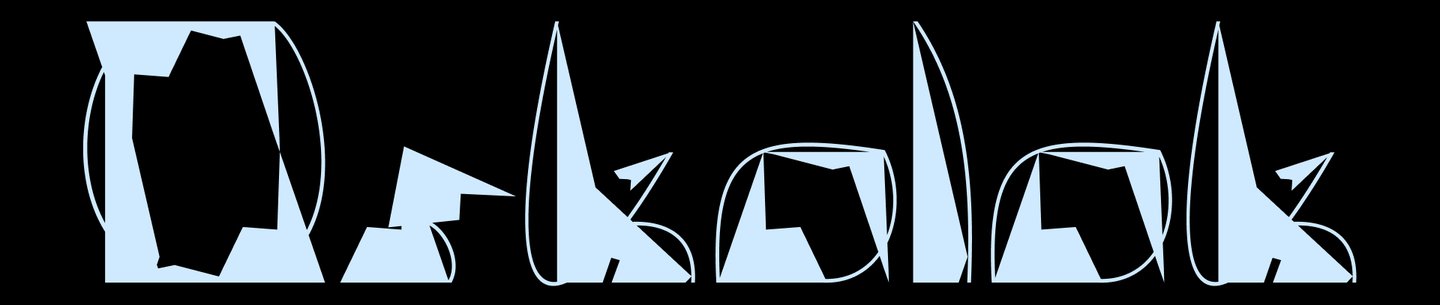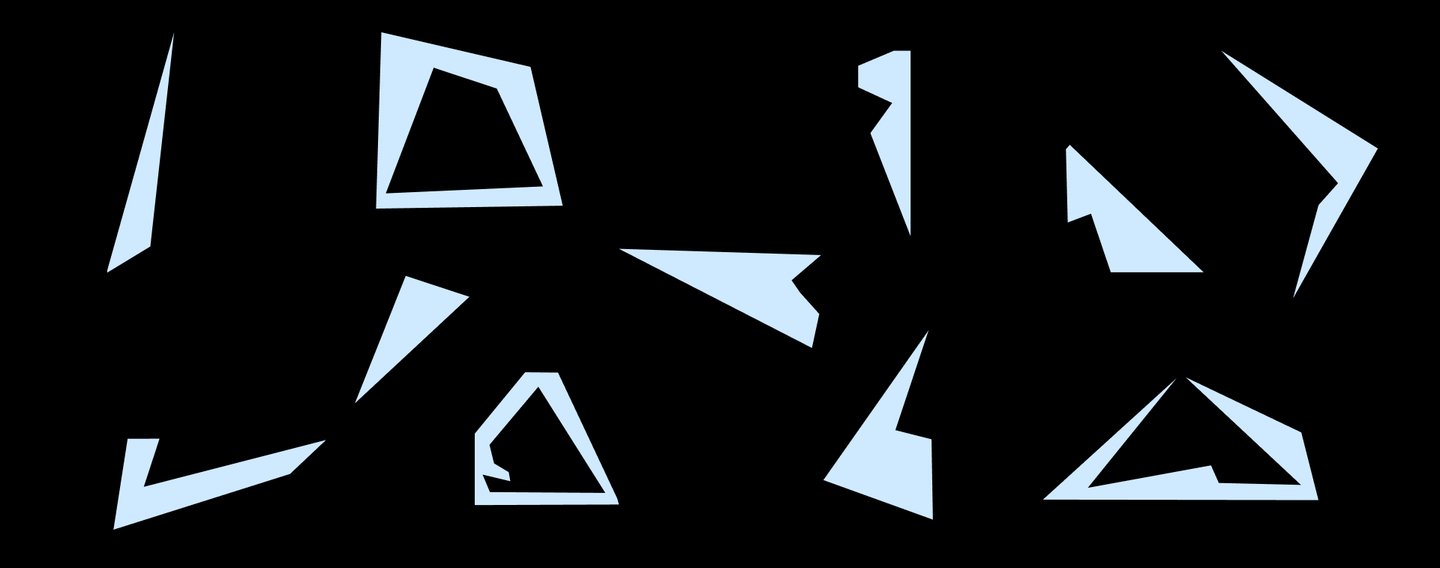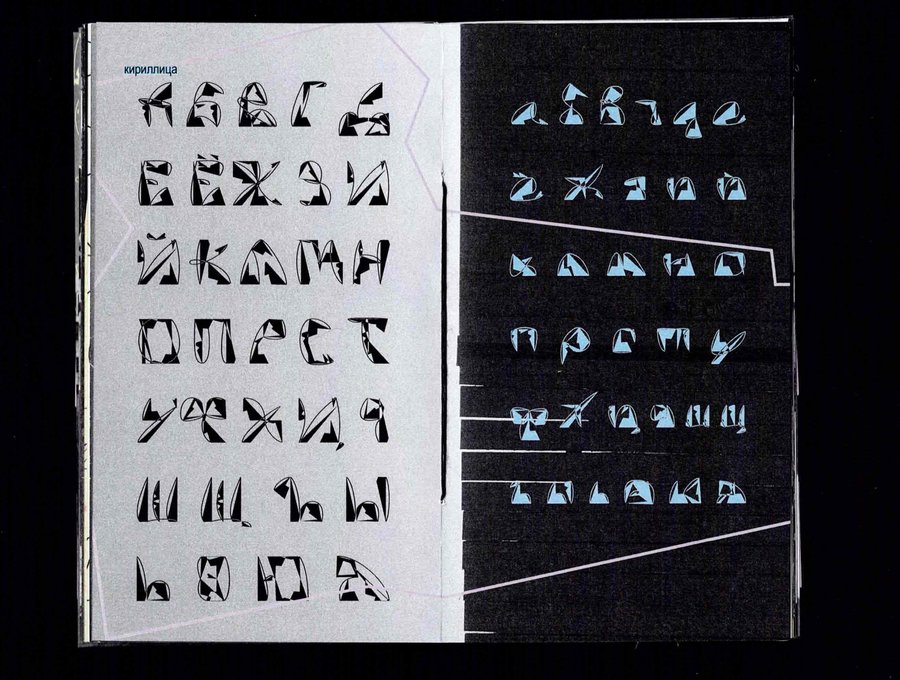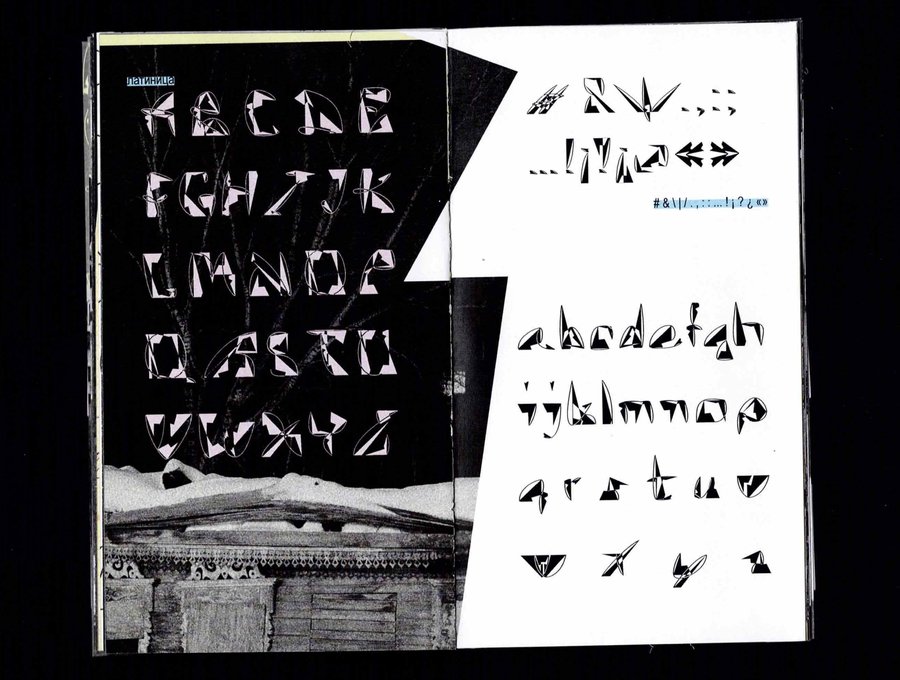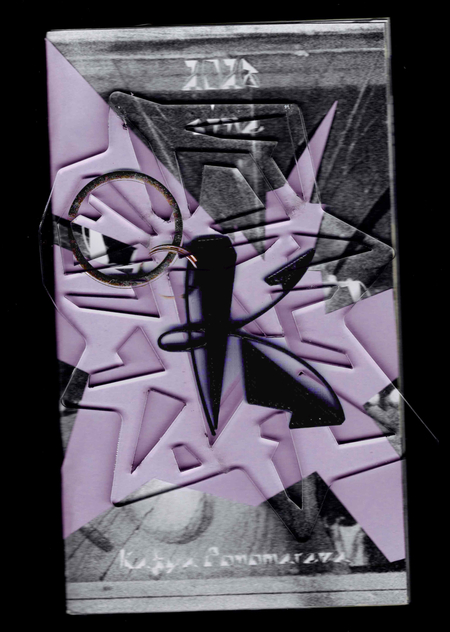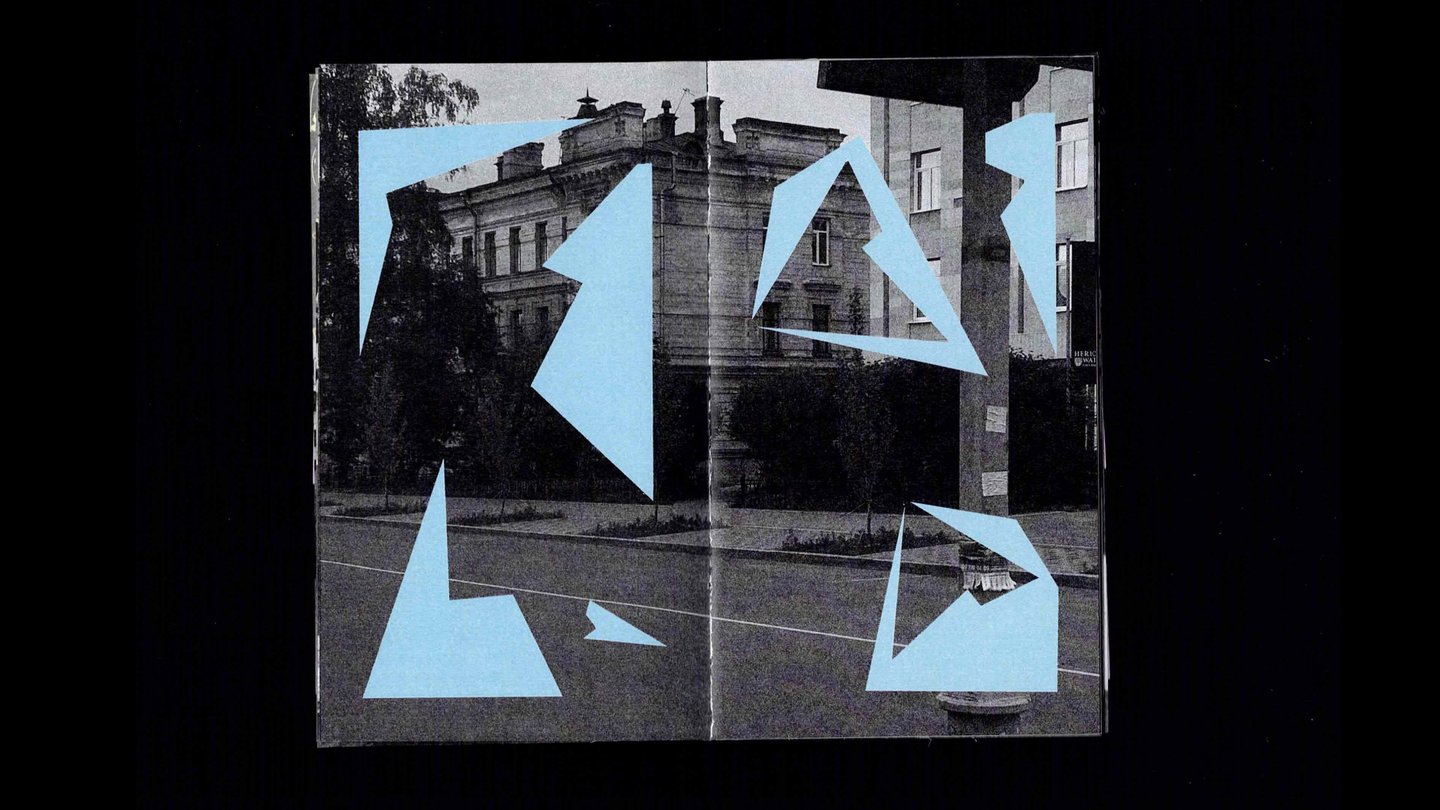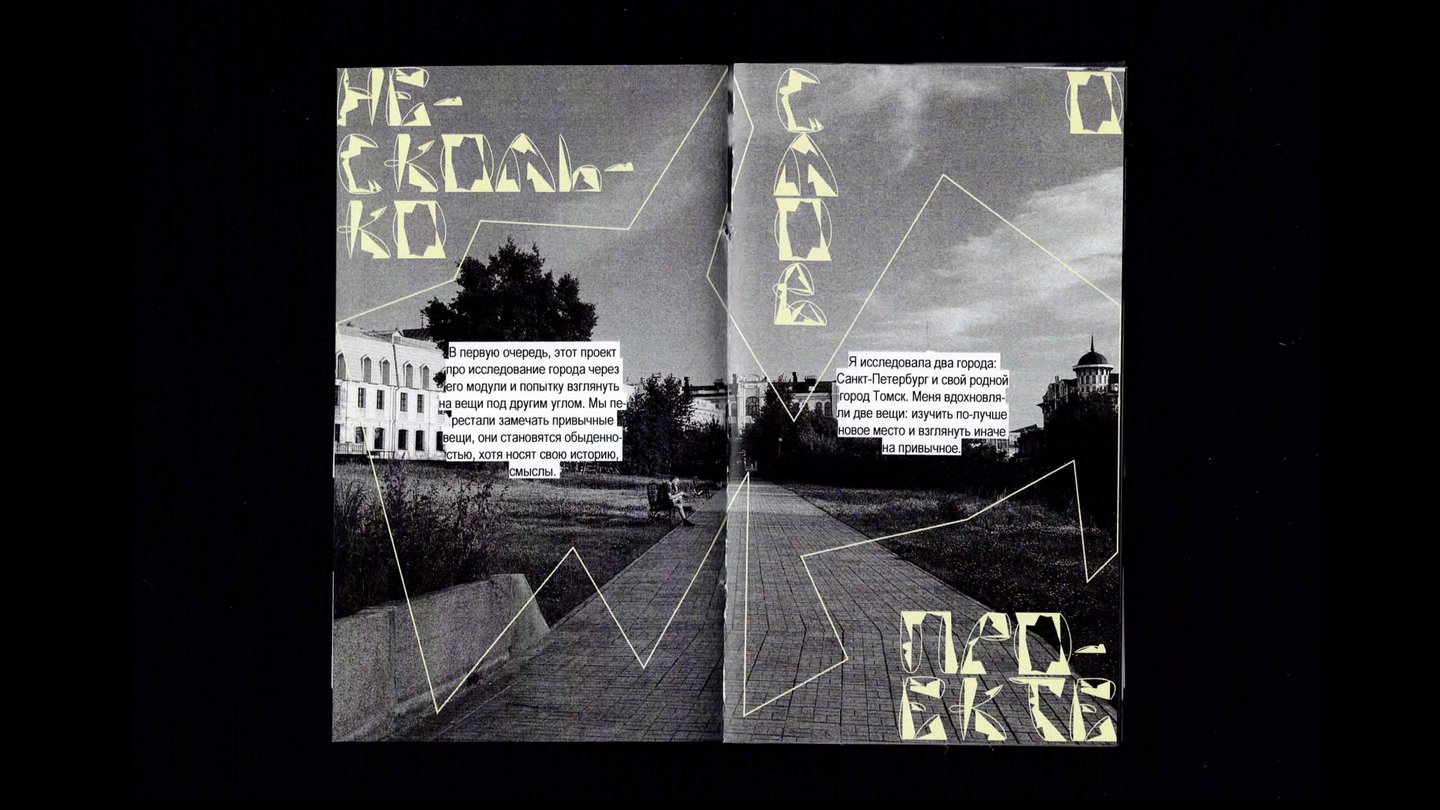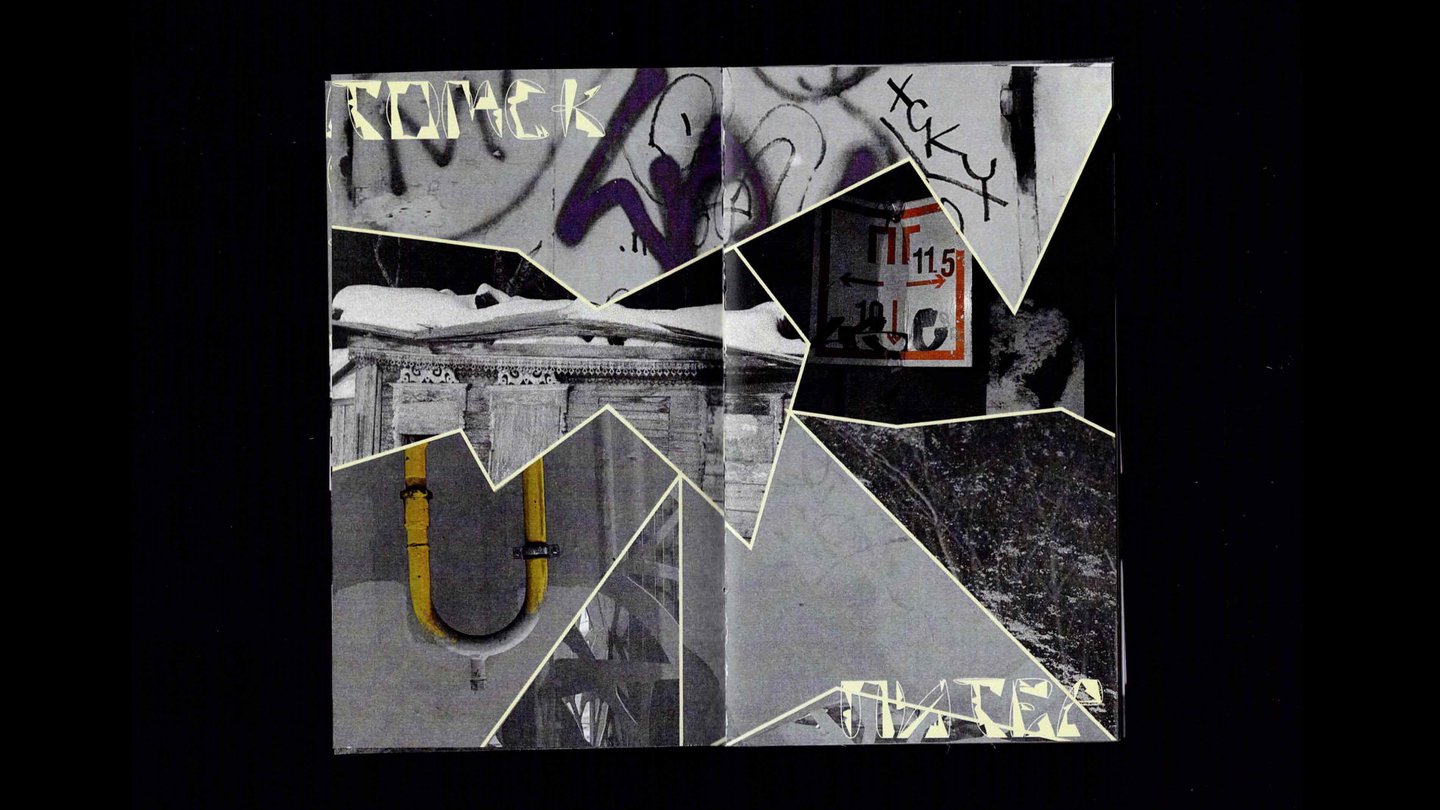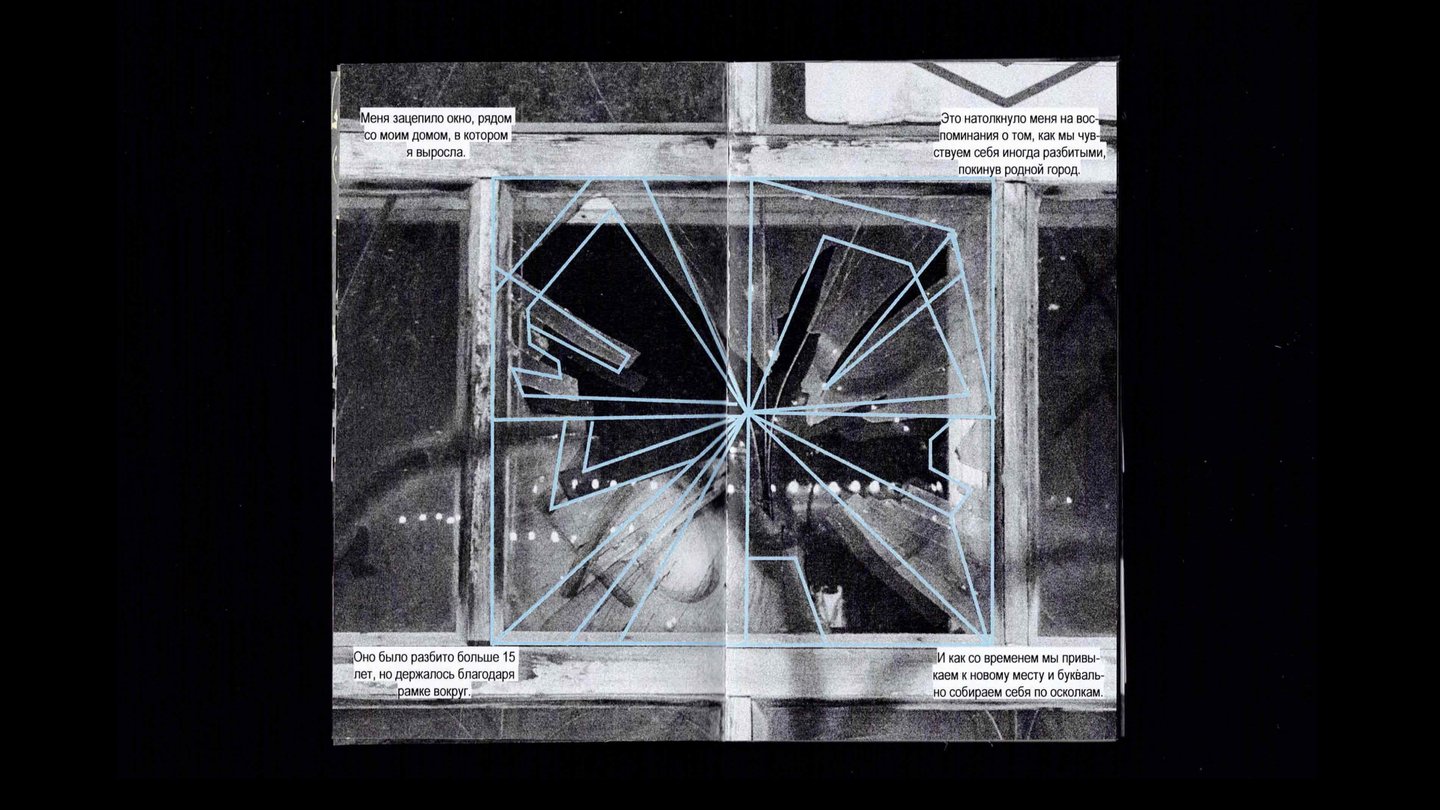
Oskolok — экспериментальный модульный шрифт, вдохновлённый формой разбитого стекла и динамикой абстрактных обрамляющих линий, символизирующих чувство, когда покидаешь свой родной город и собираешь себя по осколкам.
За основу шрифта было взято окно из моего родного города Томска, ему больше 15 лет, но он все еще держится благодаря рамке.
Из модулей собирается шрифт, осколки которого распались, но держатся и сосуществуют с линиями.
Кириллица
Латиница
Символичный брелок на память
Цифры и знаки препинания
Зин о сущности шрифта. Начало посвящено идеи появления модулей, исследованиям городов. Главная мысль: «Иногда мы чувствуем себя разбито, покидая родной город, но находим новые смыслы, собирая себя по осколкам.»
Поиски модулей, динамики
Флэт-план